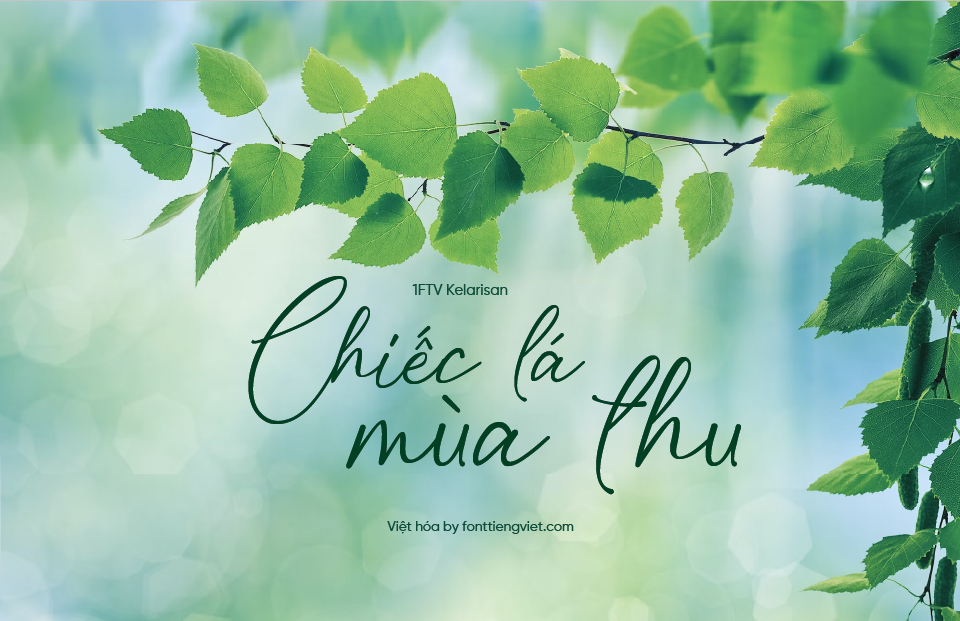
Font Việt hóa 1FTV Kelarisan
Trong thế giới thiết kế đồ họa hiện đại, việc tìm kiếm một bộ Font Miễn Phí chất lượng và hỗ trợ tiếng Việt đầy đủ luôn là ưu tiên hàng đầu của các designer. Font Việt hóa 1FTV Kelarisan nổi lên như một lựa chọn hoàn hảo dành cho những ai yêu thích phong cách tối giản nhưng không kém phần sang trọng. Với đường nét thanh mảnh và hiện đại, bộ phông chữ này giúp các tác phẩm trở nên chuyên nghiệp và tinh tế hơn bao giờ hết.
Đặc điểm nổi bật của Font Việt hóa 1FTV Kelarisan
Bộ font này được cộng đồng thiết kế đánh giá cao nhờ sự linh hoạt trong ứng dụng thực tế. Font Việt hóa 1FTV Kelarisan không chỉ sở hữu các ký tự tròn trịa, dễ nhìn mà còn được tối ưu hóa hiển thị trên nhiều nền tảng khác nhau.
Tính ứng dụng đa dạng trong học đường và đời sống
Với các bạn học sinh và giáo viên, việc sử dụng font chữ này trong các bài thuyết trình hay thiết kế báo tường sẽ tạo nên sự khác biệt rõ rệt. Khoảng cách giữa các chữ cái được căn chỉnh khoa học, giúp người đọc không bị mỏi mắt khi theo dõi những đoạn văn bản dài. Ngoài ra, phông chữ này còn cực kỳ phù hợp cho thiết kế logo, thiệp mời hoặc các ấn phẩm truyền thông sự kiện trường học.
Cách sử dụng Font Việt hóa 1FTV Kelarisan hiệu quả
Để phát huy tối đa vẻ đẹp của bộ chữ, bạn nên kết hợp nó với các màu sắc trung tính hoặc pastel nhẹ nhàng. Việc sử dụng các biến thể đậm nhạt khác nhau sẽ giúp tạo ra hệ thống phân cấp thị giác rõ ràng, giúp thông điệp truyền tải đến người xem một cách trực diện nhất.